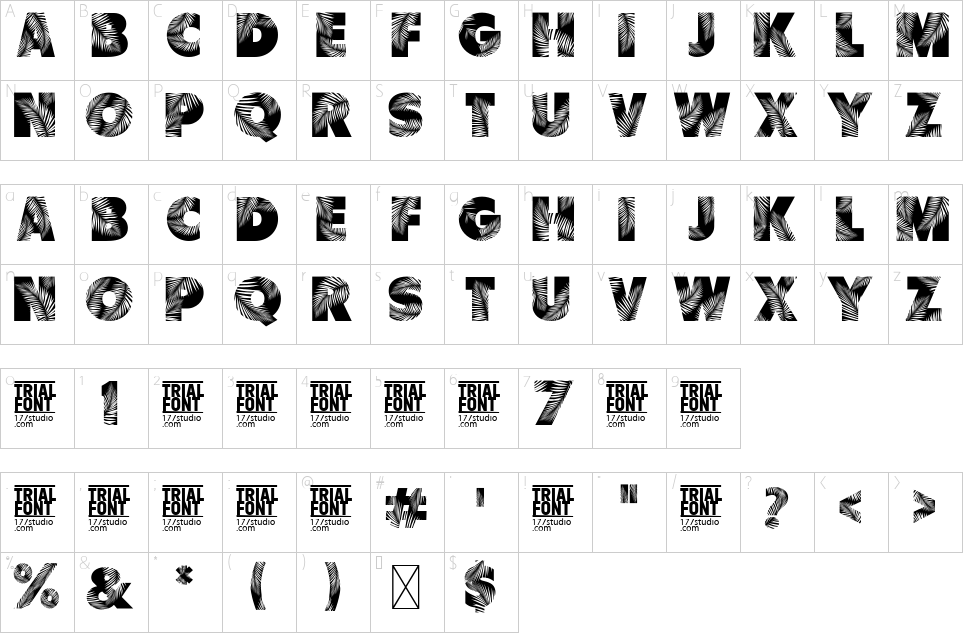
Aqui está uma descrição em português do Brasil para a página de download da fonte ‘Palm Leaf Font | 1001 Free Fonts’, seguindo os requisitos e aconselhamento fornecidos: O ‘Palm Leaf Font’ é uma fonte gratuita que incorpora o espírito do Brasil, com suas folhas de palmeira e cores vibrantes. Essa fonte foi desenvolvida por 177studio.com e já foi baixada 3.528 vezes. Com seu design moderno e natural, ela é perfeita para criar designs que refletem a rica história e cultura do Brasil. Seja para criar cartões de natal, design gráfico ou até mesmo para personalizar sua própria identidade visual, esta fonte oferece uma variedade de opções para expressar seu próprio estilo. Não perca tempo e entre em contato com sua criatividade, baixando ‘Palm Leaf Font’ hoje.